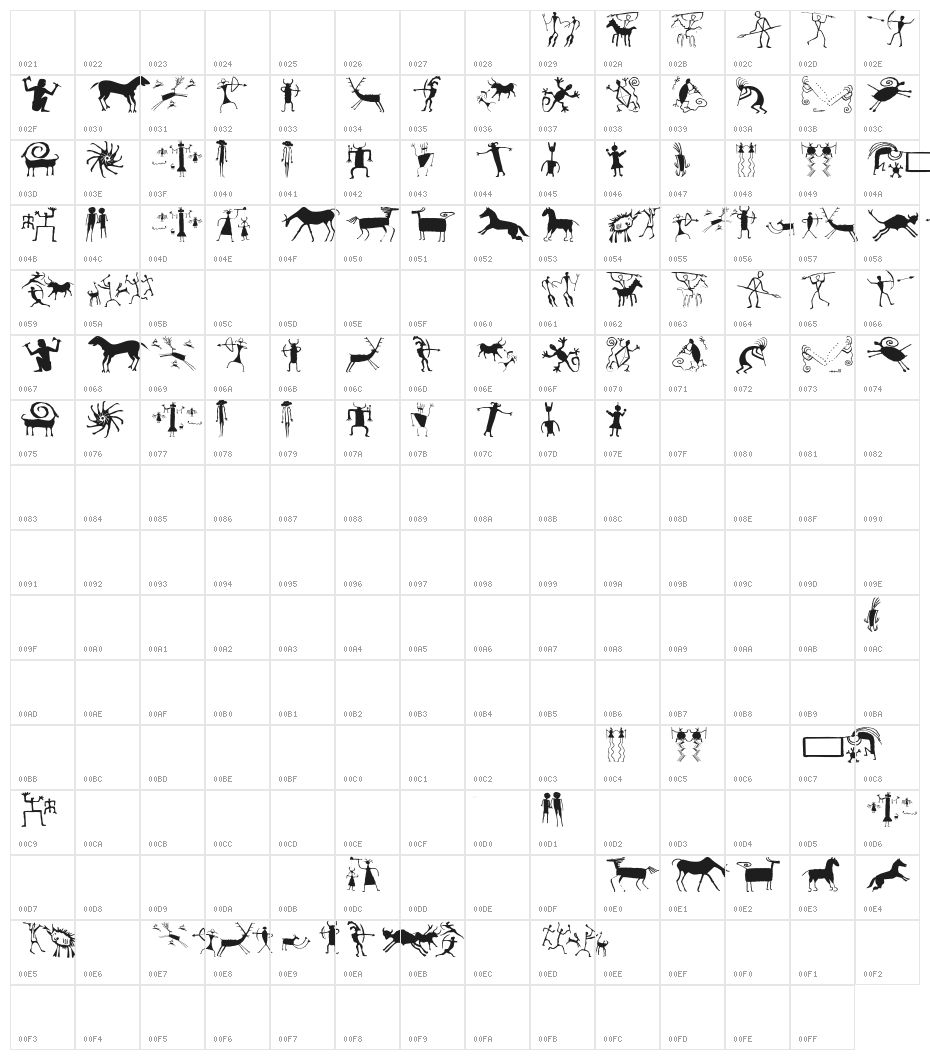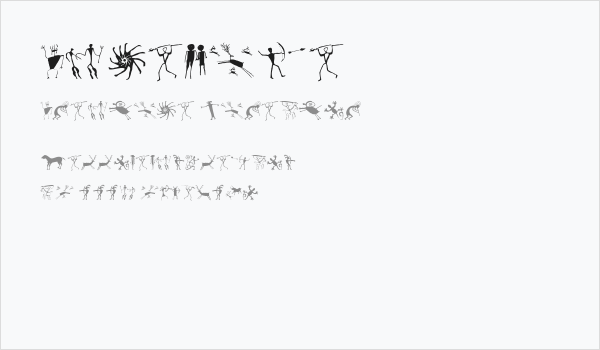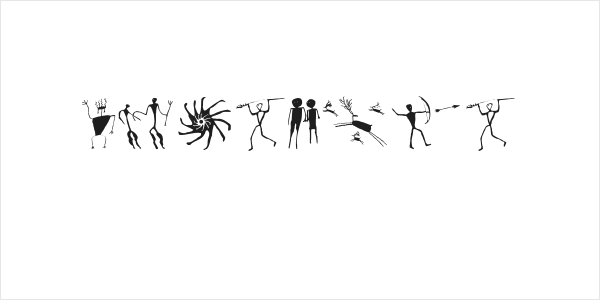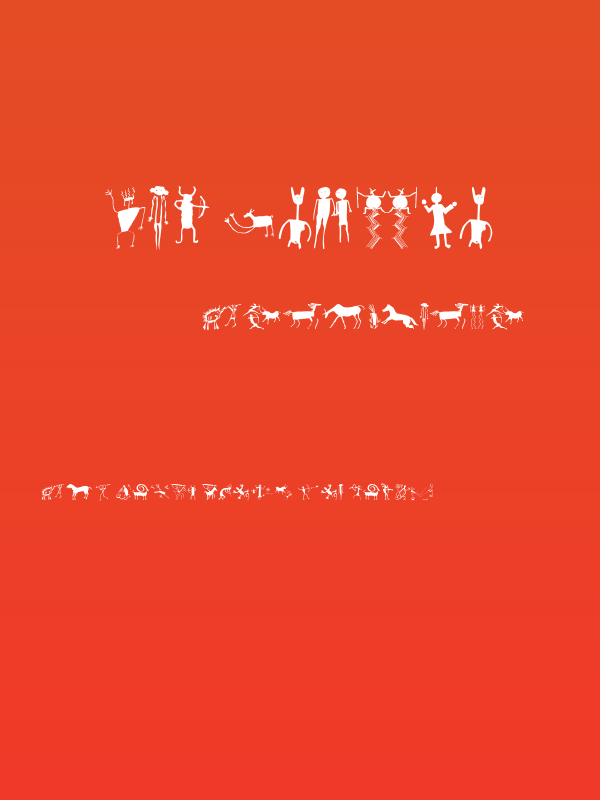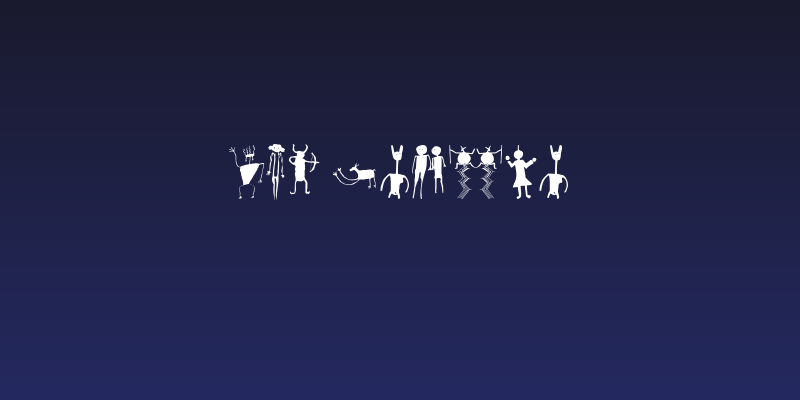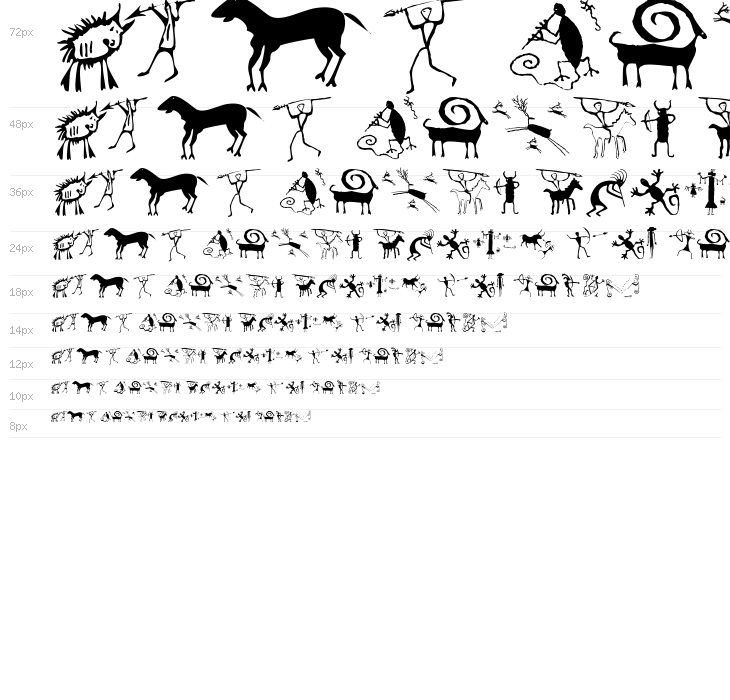
CaveLife Font
| Gesamtstil | Vintage |
| Anwendungsfall | Logos, Artistic projects, Educational materials |
| Vorgeschlagene Projekte | Ideal for historical documentaries, educational materials, themed event posters, and artistic projects that require a touch of ancient culture. |